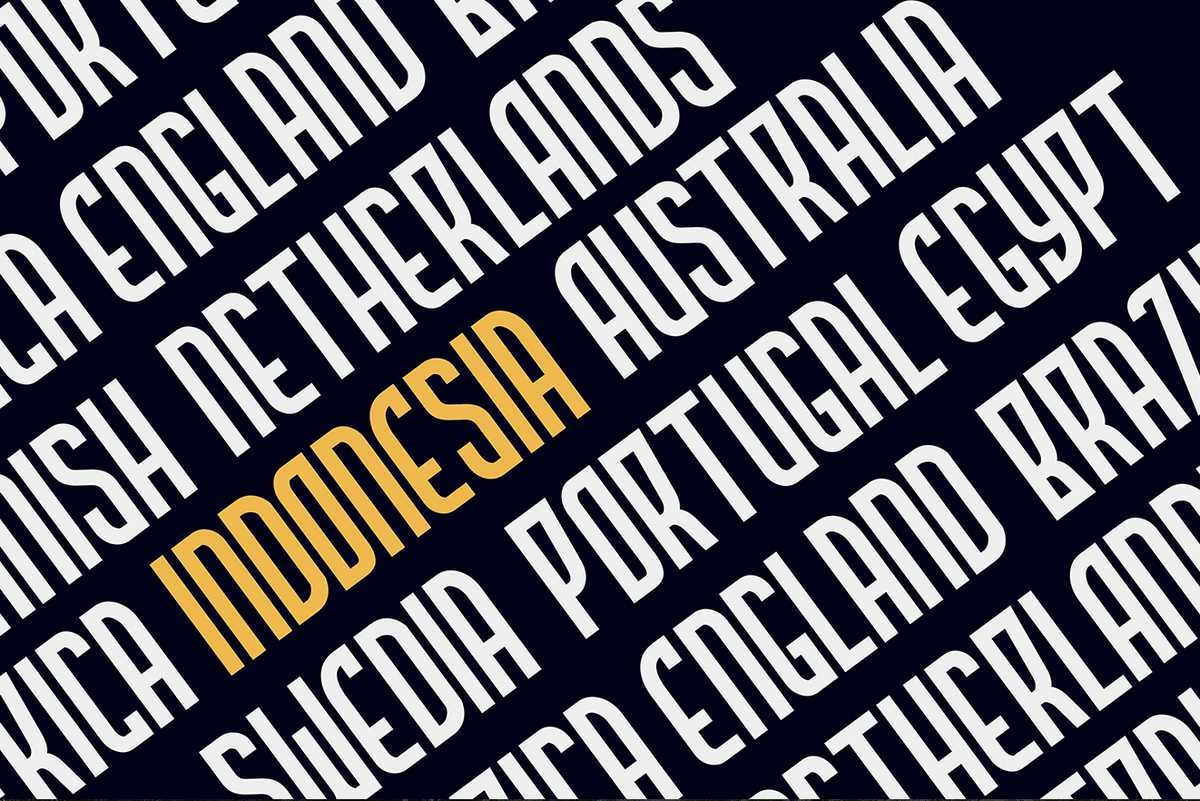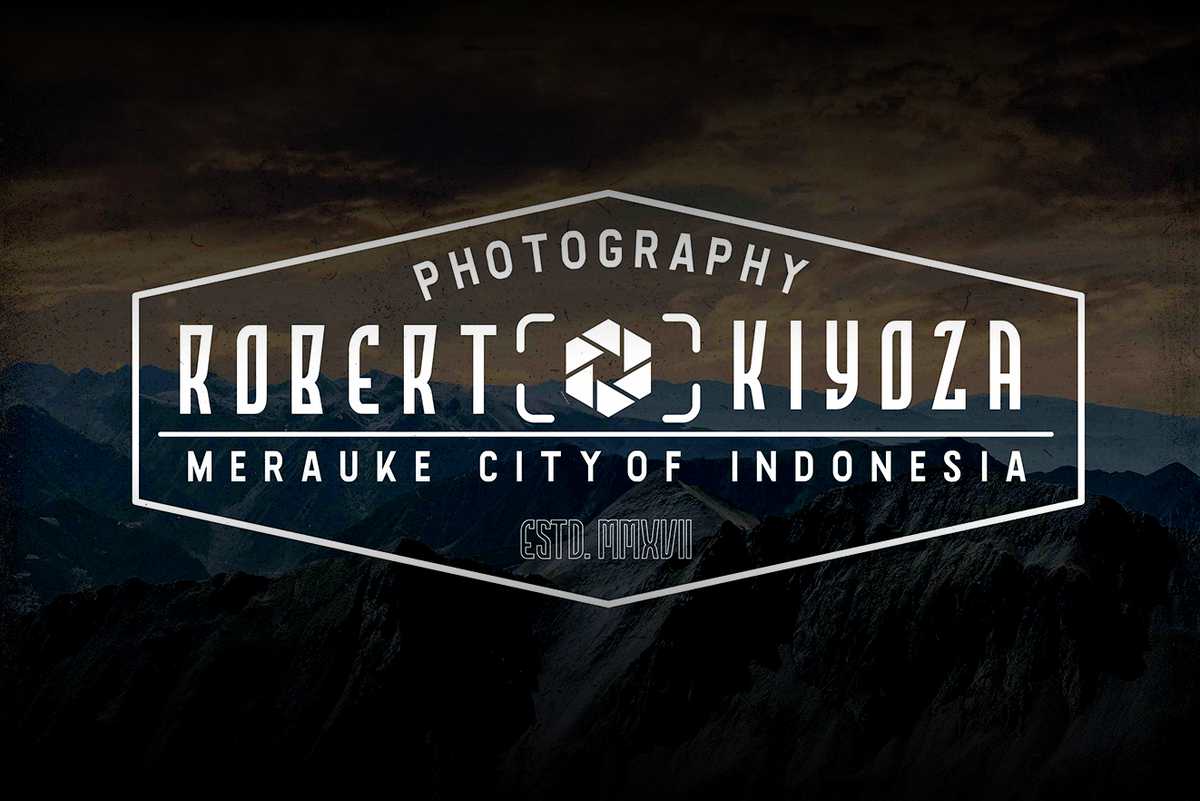
介绍风格更好的Highstories Family。这是您设计中风格有趣、风格独特的最佳Font系列,无论您的各种作品如何,都能让您的作品看起来坚固、轻松,最适合海报、品牌、标识、t恤设计产品设计,包装和报价以及更多。介绍具有更好的包装风格的Highstories Family。这是一款具有有趣风格且在您的设计中完美融合的最佳FontCollection,您的各种作品都能让您的文字看起来坚固、方便,最适合海报、品牌、标识、t恤设计、产品设计、包装和报价等。